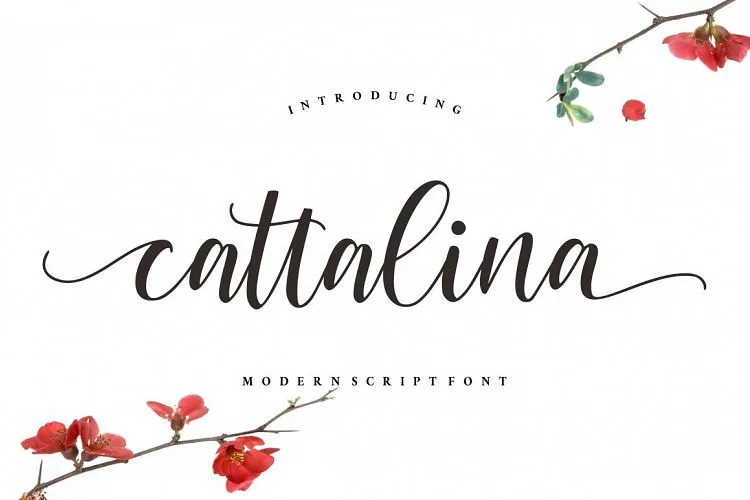
Esta fonte ‘Cattalina Script’ é uma delicada combinação do modernismo e da escrita à mão real. Cada letra foi cuidadosamente moldada para garantir que sua mensagem fique sempre linda, seja na publicidade ou nos postagens de redes sociais. É perfeito para criar um toque de handlettering em qualquer projeto de design. ‘Cattalina Script’ é uma opção elegante e naturalmente feita à mão, projetada pela Good Java Studio. Perfeita tanto para logotipos quanto para cartões de convite ou materiais de estaçãoeria, ela é ideal para casamentos e eventos especiais, desde embalagens de produtos até até fotografia. Suas linhas suaves e personalizadas tornam esta fonte uma escolha perfeita para quem procura algo mais do que um simples tipo tipográfico. Ela também pode ser usada em marcações ou outros materiais especiais necessitando de um toque pessoal e sofisticado.